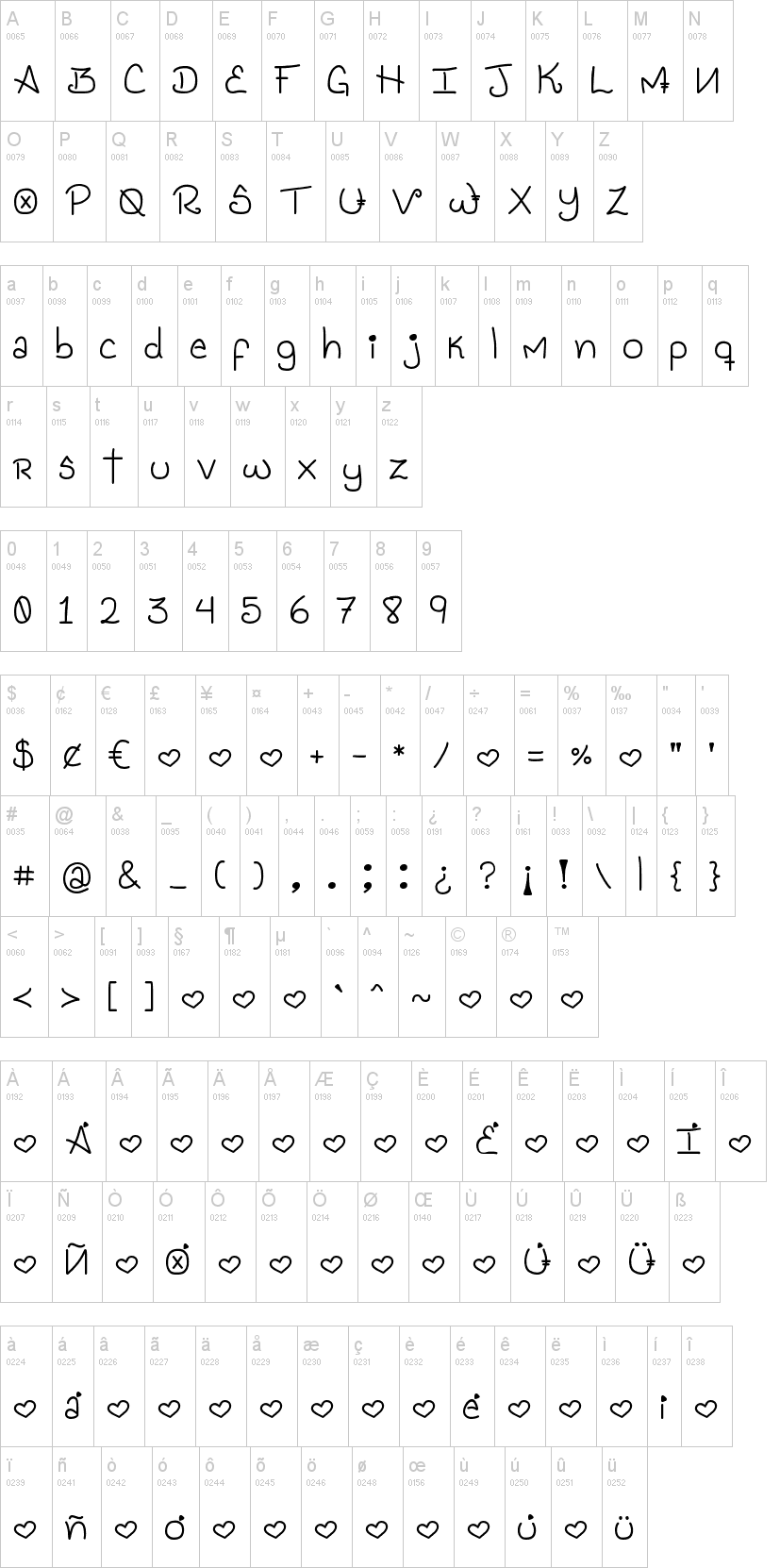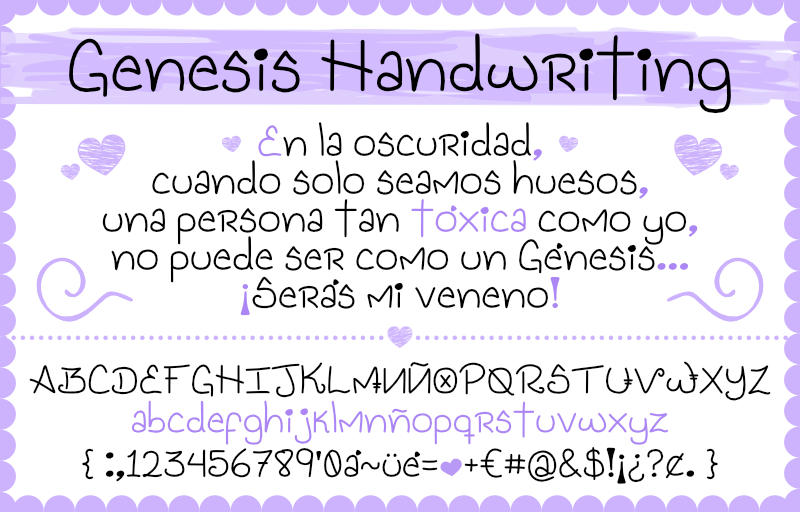
Note of the authorLa font se basa en mi escritura a mano, pero está creada únicamente con mouse.
The font is based on my handwriting, but is created with a mouse only.